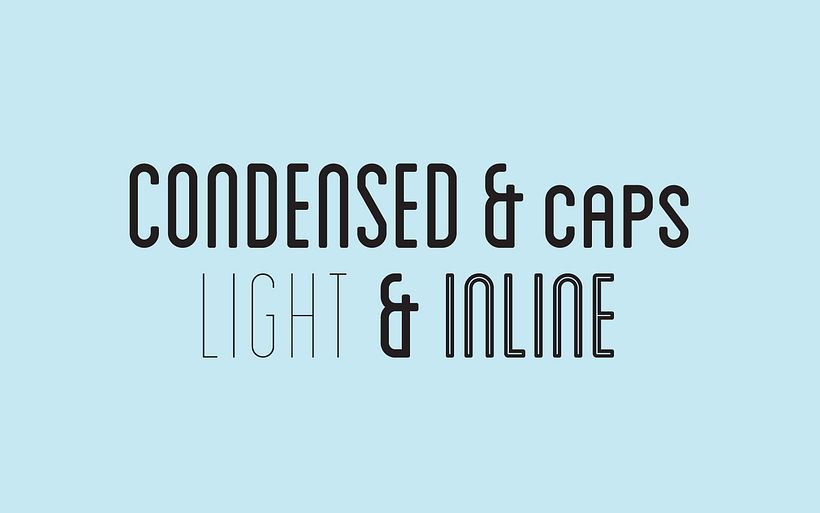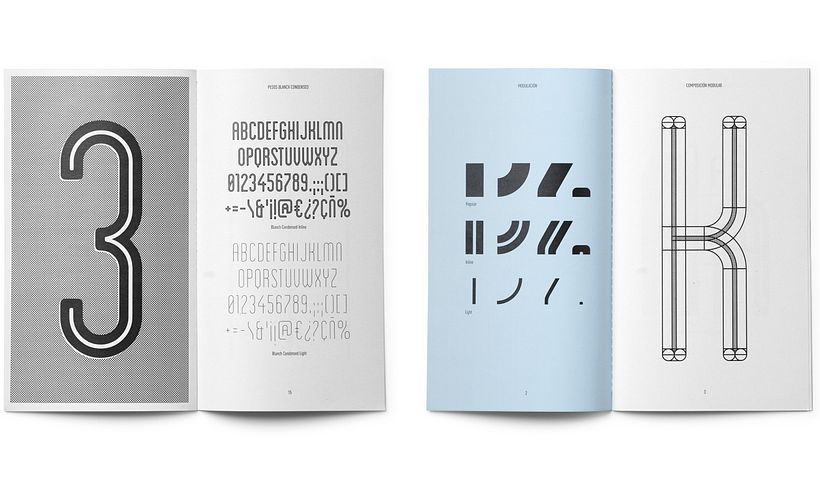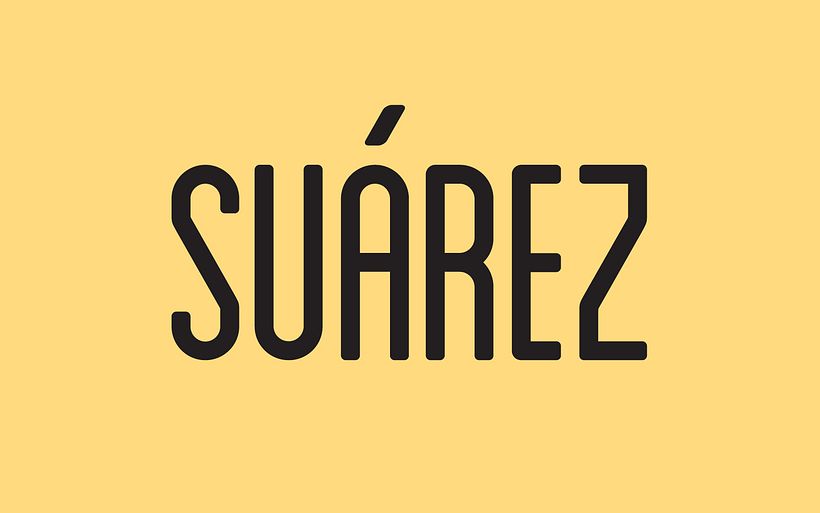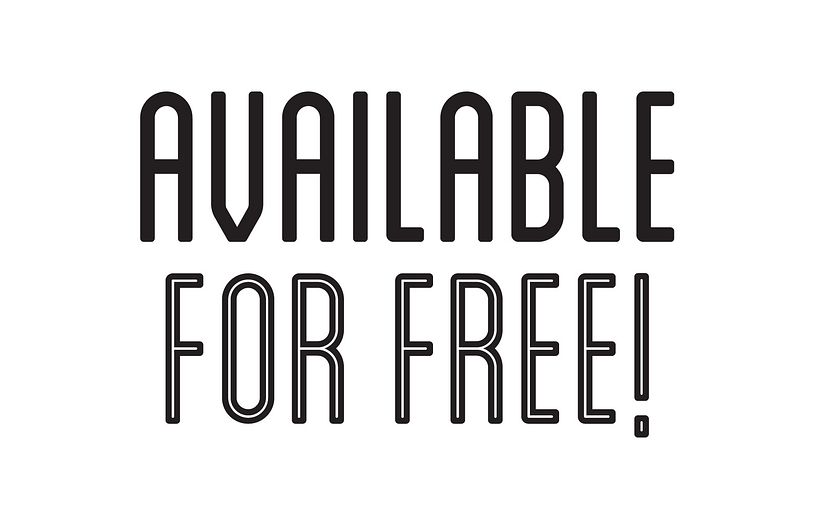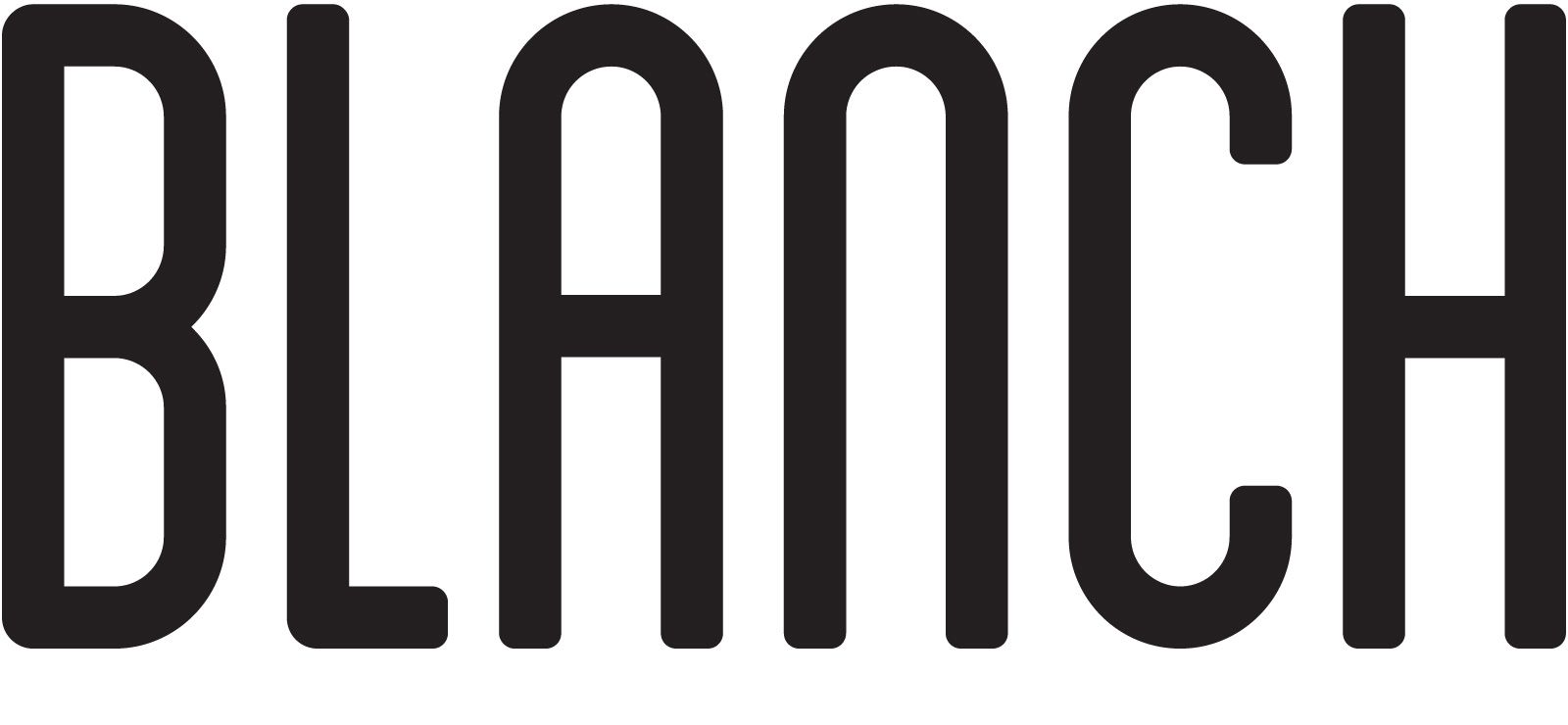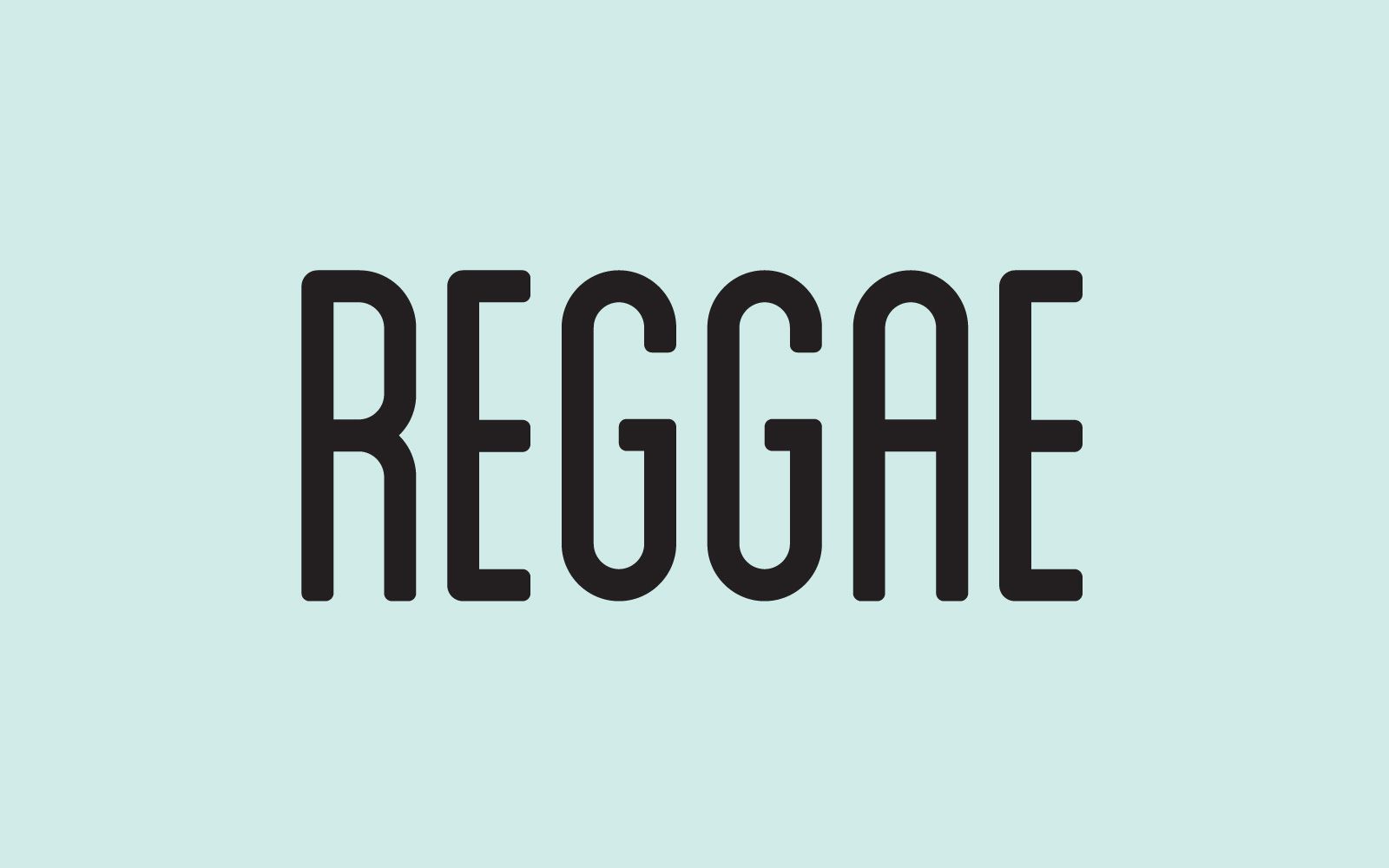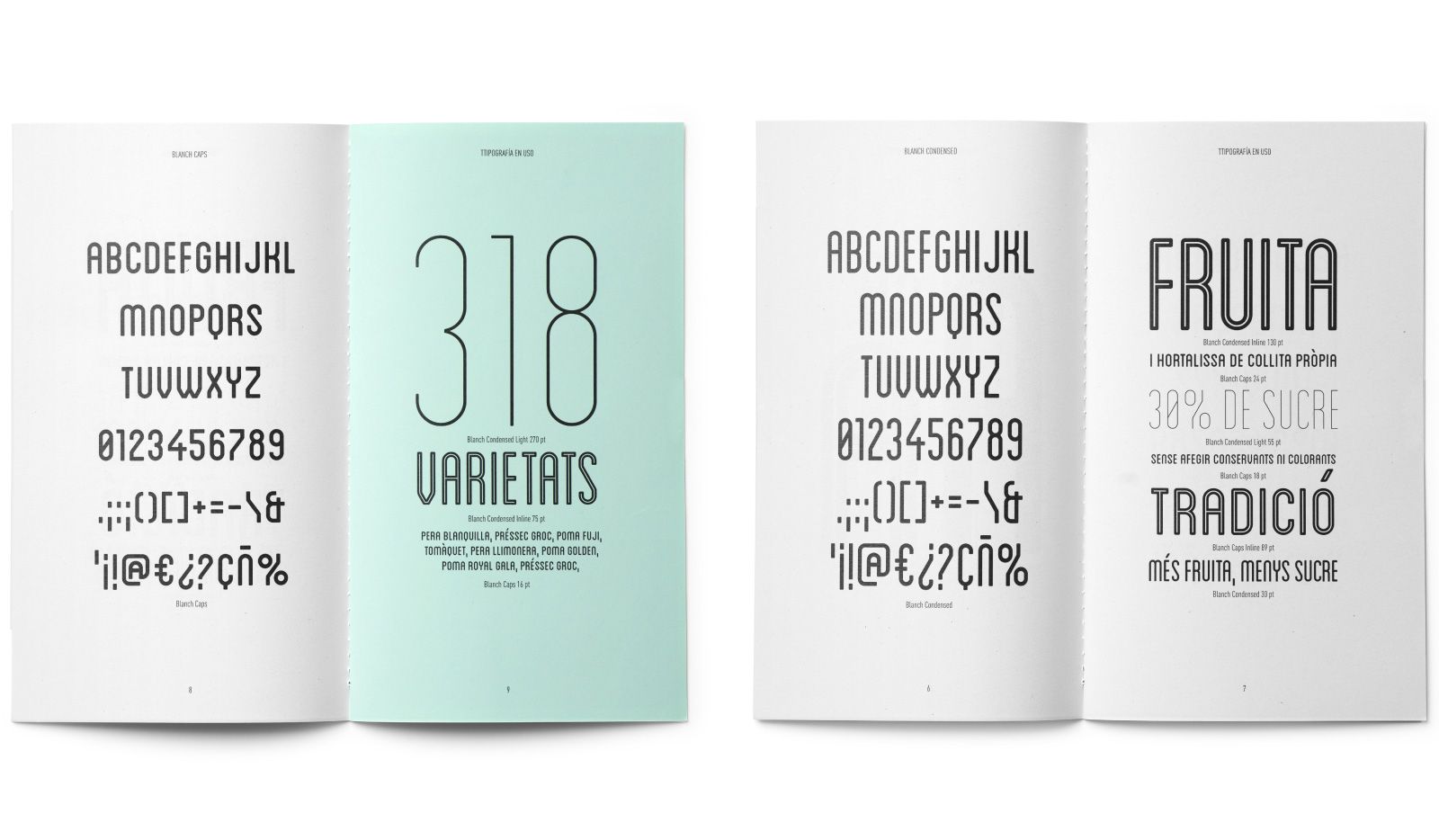
Blanch Font
by Atipus @atipus
This is a modular typeface family that's halfway between a 1950s-inspired sans-serif and the numeric character set used by most labeling machines. These seemingly opposing concepts create an atypical typography.
Se trata de una familia tipográfica modular a medio camino entre un palo seco de inspiración 50’s y el juego de caracteres numéricos que utilizan la mayoría de máquinas etiquetadoras. Conceptos aparentemente antagónicos que confieren una tipografía atípica.